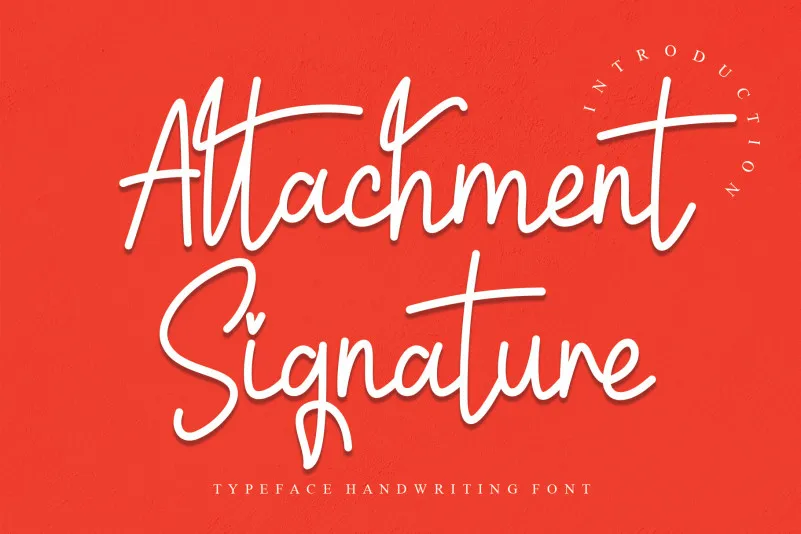
Attachment Signature Script Font – Fonte Grátis
Attachment Signature Script Font
Esta fonte ‘Attachment Signature Script Font’ é criada pelo designer creativeletter para quem busca uma experiência única na tipografia. Ela oferece um toque especial ao escrever e assinar, com linhas suaves e gráficos fluidos que imitam autógrafos cuidadosamente escritos. Com seu estilo script elegante e sua facilidade de uso, essa fonte é perfeita para aqueles que valorizam uma mão-dura em seus documentos pessoais ou profissionais. A experiência de usar esta fonte não se limita apenas à aparência; ela promete dar um toque especial ao seu design gráfico ou escritório digital. Seja para assinaturas, cartas pessoais ou até mesmo para criar o seu próprio estilo único, essa fonte é uma ótima escolha.